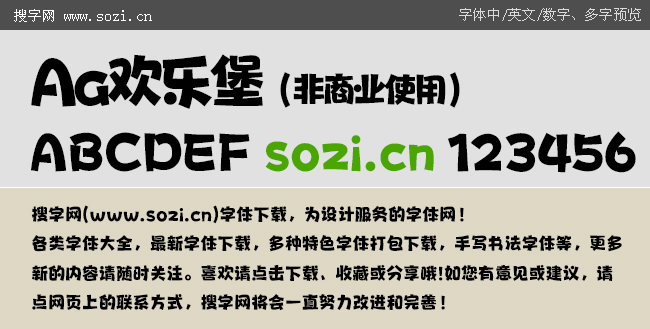
Aa歡樂堡
搜字網(wǎng)給大家提供一款A(yù)a歡樂堡(非商業(yè)使用)中文字體下載,該字體是一款手寫風(fēng)格的卡通字體,字體筆觸粗實,字形圓潤可愛,具有很好的視覺感,適用于平面宣傳設(shè)計、網(wǎng)頁設(shè)計、海報設(shè)計等應(yīng)用(此字體為個人非商用版,商用可以聯(lián)系QQ:1006760504)。